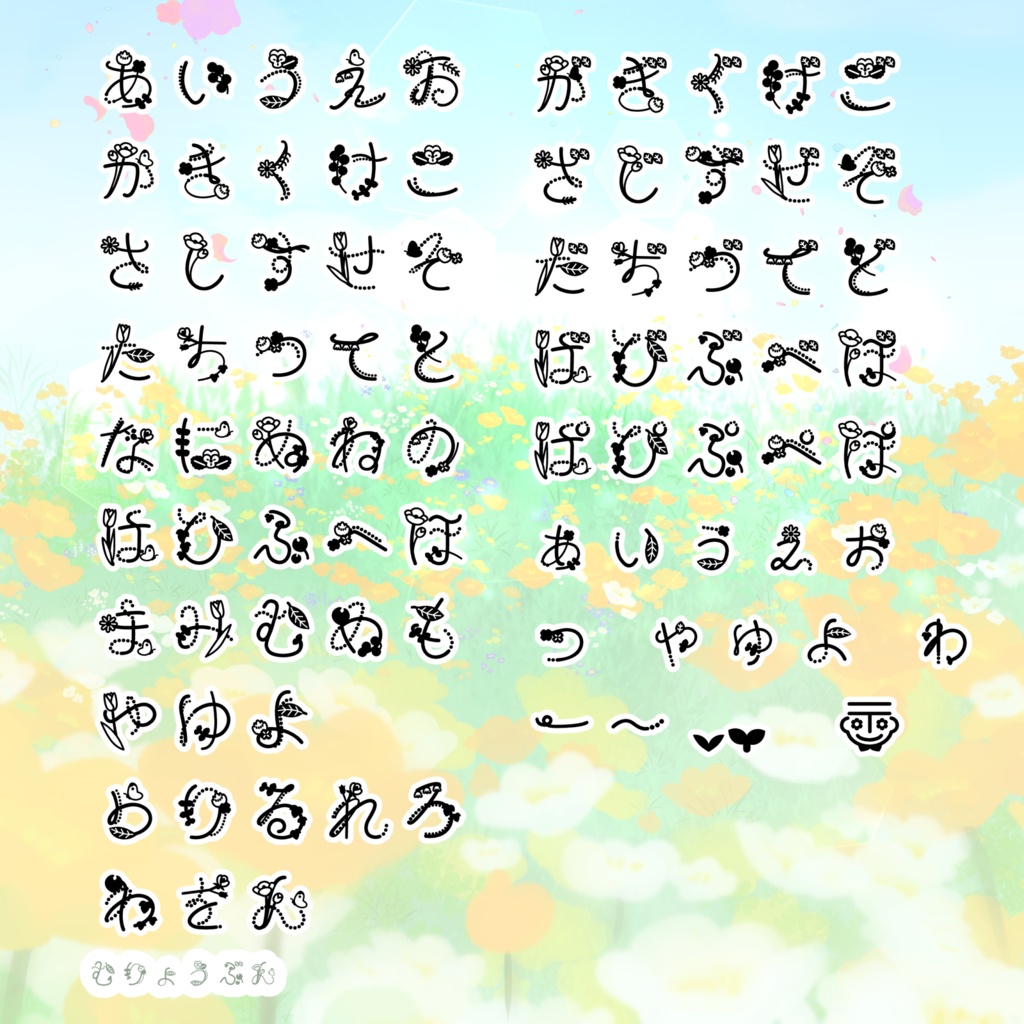
フリーフォント/はながさいたら。
花がデザインされたフリーフォントです。 ひらがな 、。ー~〠が変換可能です。 商用、同人、その他 制作にお役立てください。 年齢制限のあるもの、無いものの区別はなく自由にお使いいただければと思います。 たくさん使っていただけると報われます。 ------------ 以下、他ECサイトさんへお取り扱い頂くにあたり、2024/10月に加筆された事項です。 大きな変化はありませんが許可と禁止の内容が具体的になっております。 ▶許可 ・違法性さえなければ、商用から個人まで幅広く利用が可能です。 ・年齢制限のあるもの、無いものの区別はなく自由にお使いいただけます。 ・動画、同人活動、商品のタイトルロゴ、見出し、推し活 創作活動全てにお好きに利用が可能です。 ・RPGやノベルゲームなどのアプリにてセリフや表示文字への利用もぜひお願いします。 たくさん使っていただけると報われます。 ・創作に当たり、購入者様(無料ダウンロード者様も含む)のみが使用可能な状態でのWEB上ソフトウェアへのアップロード ・創作に当たり、購入者様(無料ダウンロードも含む)のみが使用可能な状態でのオンラインサーバーへのアップロード こちらも問題ありません。 ※ご使用のサイトがご本人のみ利用可能であることをご確認してからアップロードをお願いいたします。 ・企業で共有してフォントをお使い頂く場合、下記の譲渡には入りませんが、あまりにも頻繁に複数人でご利用いただく場合は個々での購入願います。 同時稼働2PC、2アカウントを目安にお願いします。 (出来れば書体ではなくアウトラインをとるなどで共有してください) ▶禁止 ・AI学習への取り込み ・当フォントデーターをダウンロードしたご本人様以外のユーザーが自由に文字制作に利用可能な環境のWEB上へアップロードする行為 (下記の配布に該当します) ・こちらのフォンの文字を”文字デザイン”としてグッズ化やスタンプ化して販売・頒布する行為(その場合は制作者に案件としてご連絡ください) ※弊フォントをタイトルやネーミングロゴに採用し、それをグッズ化しても、これには該当しません。 ・お絵かきアプリやWEB上ソフトウェアで全ユーザー向けに利用可にしたい場合(是非、制作者に案件としてご連絡ください) ・こちらのフォントのデザインをロゴとして商標登録する。 ・フォントデータの譲渡・配布・転売。 ・誹謗中傷する様な迷惑行為に弊フォントを利用する。 弊フォントを使用し発生したトラブル等に責任は負えませんのでその点を重々ご理解ください。 フォントの著作権は略delic.にあります。 「本ファイルは武蔵システム(https://opentype.jp/)の(フォントエディタ OTEdit for Windows)を使って作成しました。」 2024.10.28/略delic. なにかご用がある場合は booth上にあるメッセージマークからのお問い合わせ下さい。リアクションが最も早いです。